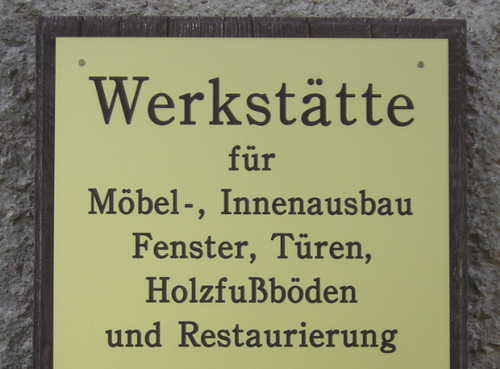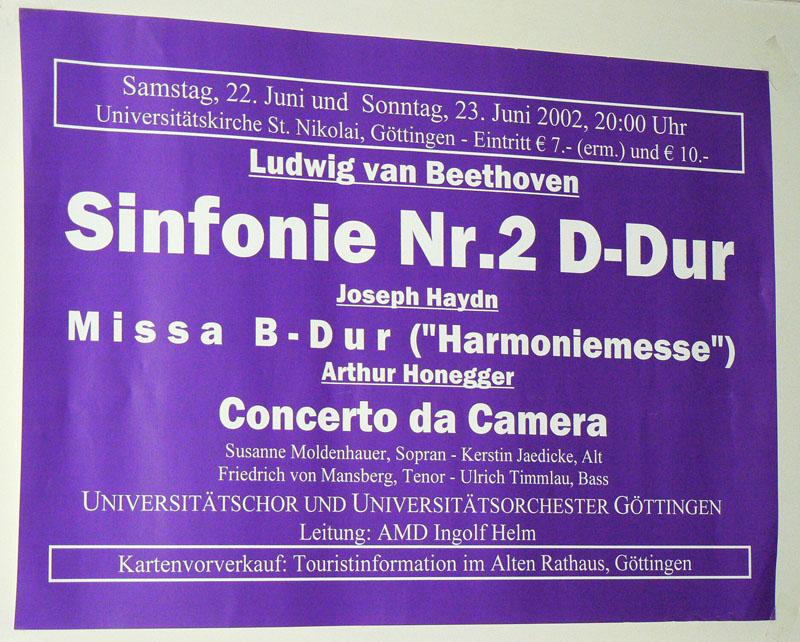
Da der Typo-Sünden-Thread gesperrt ist und ich mich nicht im Wiki anmelden will, andererseits aber der Überzeugung bin, daß ein solcher Thread für ein solches Forum unabdingbar ist, hier Teil II:
Hat sich doch schon gelohnt, oder? Aber wenigstens das ? stimmt einigermaßen.
… und warum diese Firma die Zeitläufte nicht überstanden zu haben scheint, muß seine Ursache auch nicht unbedingt nur in der strukturschwachen Region Weißenfels haben.
Was ist denn das für ein Zeichen? Woher haben die das? Ein B scheint es nicht zu sein.
Wer findet die meisten Fehler?
Nur Typo oder auch Rechtschreibung / Grammatik? Zählt jedes falsche Divis einzeln als Fehler?
Ach, das war eigentlich nur so daher gesagt. Aber ich will niemanden in seinem Eifer bremsen. Von daher schlag ich vor, dass Rechtschreibung/Grammatik und alle Divis-Fehler einzeln aufzuzählen sind. :tutor:
Vor allem was ist das für eine Schrift? Die hat so ein paar schöne diagonale Elemente, die sie recht interessant machen
Alpha
Die Schrift koennte die Century Old Style sein.
Allerdings ist es durchaus moeglich, dass die hier nur als Vorlage gedient hat und das, was Du auf dem Schild siehst ist eine mehrzuegige Gravierschrift. Kommt mir jedenfalls so vor, wenn ich mir die abweichenden Strichstaerken bei den Minuskeln anschaue.
Z.B. "lzf" bei Holzfussboeden.
Ich glaube Du hast recht. Aber wo das ß herkommt weiss der Teulfel.
Also ich hab jeden falschen Abstand vor und nach jedem falsche Divis und jeden Rechtschreib- und Grammatik fehler gezählt. Kann sein, dass ich mich verzählt hab, auf alle Fälle sind es mehr als 20 Fehler.
sieht man eigentlich, daß Abstände vor und nach dem Gedankenstrich zwingend nötig sind,da sonst Uhr—20.00 enger aufeinanderhängt als 13.00 Uhr bzw. 20.00 Uhr. Das ist erstens ein grober Logikbruch, zweitens ziemlich lesefeindlich und daher: schlechte Typographie.
Ich bin jedenfalls über 9 Fehler nicht hinausgekommen.
Die Abstaende vor und nach dem "Devis" brauchts eigentlich schon deshalb zwingend, weil ja eigentlich 13.00 Uhr "bis" 20.00 Uhr dasteht.
Ich komme ansonsten auch auf 9 Fehler. Auch wenn die ganze Tafel nach der Aenderung der Oeffnungszeiten jetzt etwas seltsam ausschaut :D
Bis-Zeichen: 1830–1905
20–22 Uhr
:!: Ohne Leerzeichen, aber so oder so, 13.00 Uhr – 20.00 Uhr sieht irgend wie doppelt gemoppelt aus, ich hätte das ganze auf die Schreibweise des Typowikis umgestellt, oder Uhr weggelassen, da dies sowieso aus dem Kontext klar wird.
Wenn die Zeiten so geschrieben waeren wie im T-Wiki, dann ja. Ich wuerde im Normalfall auch das .00 weglassen, weil das hier, zumindest fuer mich, keinerlei Informationswert hat.
Also so wie im Wiki 13-20 Uhr.
Aber mit Uhr so: 13 Uhr - 20 Uhr.
Fuer mich wuerde sich sonst eine Einheit "Uhr-20" ergeben. Hier kaeme bei mir ein Halbgeviert vor und nach den En-Strich.
Ah, jetzt komme ich endlich mal dazu, dieses Glanzstück typografischer Ausgestaltung zu zeigen. Ein echtes Gruselkabinett! Auf wie viele Fehler kommt Ihr hier?
Was moechtest Du denn als Fehler gezaehlt haben? Bei der Auswahl.
Ausserdem koenntest Du Dich ja wenigstens freuen, dass sie den Honegger richtig geschrieben haben :hammer:
Was moechtest Du denn als Fehler gezaehlt haben?
Kannst ja mal mit echten Fehlern anfangen, von da aus können wir uns dann über die übleren Gestaltungssünden zu den Feinheiten vorarbeiten! :mrgreen:
Darauf, daß sie »Honegger« richtig geschrieben haben, habe ich schon persönlich geachtet, ich war nämlich Solist in dem Konzert. Bei der Ausarbeitung des Plakates war ich allerdings nicht beteiligt und war dementsprechend dann letztlich doch ganz froh, daß sie meinen Namen und den Namen meiner Flöten-Kollegin dann vergessen haben … :twisted:
Im Stark-Verlag verwendet man auch bloß Zollzeichen statt Anführungsstrichen, hatte jetzt keine Lust das einzuscannen.
Und hier ein Ausschnitt aus einem Lateinmerkblatt.
Darauf, daß sie »Honegger« richtig geschrieben haben, habe ich schon persönlich geachtet,
Meine Anspielung auf Honegger war etwas missverstaendlich. Auf die Idee, dass jemand ja auch an "Erich" gedacht haben koennte bin ich erst spaeter gekommen :)
Ich hatte dabei an Arthur mit H gedacht und das aus einem konkreten Grund.
Ein Bekannter von mir heisst ebenfalls Arthur mit H und wurde vor einiger Zeit von seiner Sachbearbeiterin beim Finanzamt darauf angsprochen, ob er denn, nach der Rechtschreibreform, das H in seinem Namen noch benoetigt, da doch jetzt diese ganzen TH auch einfach als T geschrieben werden koennten - siehe Thunfisch :lol:
Am meisten an dem Plakat hat mich ja die ("Harmoniemesse") beeindruckt.
Ein Bekannter von mir heisst ebenfalls Arthur mit H und wurde vor einiger Zeit von seiner Sachbearbeiterin beim Finanzamt darauf angsprochen, ob er denn, nach der Rechtschreibreform, das H in seinem Namen noch benoetigt, da doch jetzt diese ganzen TH auch einfach als T geschrieben werden koennten - siehe Thunfisch
Das wäre der Punkt, wo ich die Geschäftsbeziehung zu diesem Amt aufkündigen würde.